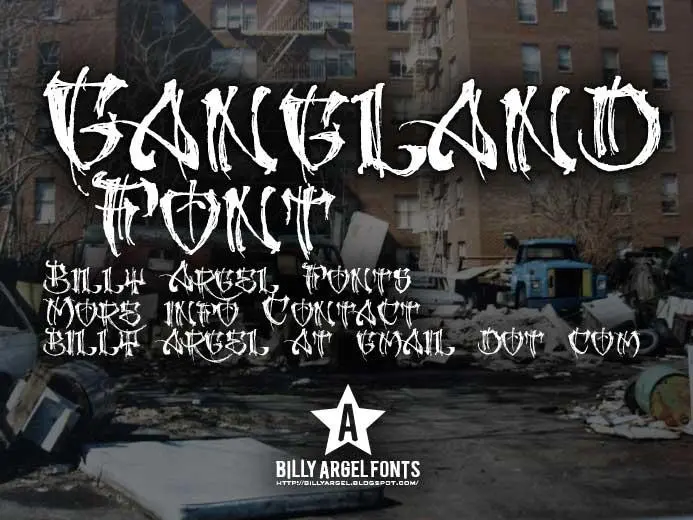
A GANGLAND Font é uma elegante fonte Brush, criada pelo designer Hamilton. Ela traz uma mistura única de sofisticação e liberdade artística para qualquer projeto que você escolha adicionar à sua portfolio. Com traços suaves e leves, esta fonte oferece um toque autêntico e pessoal a suas criações. Perfeita tanto para títulos quanto para o texto interno de um design, ela também se adequa perfeitamente a logotipos criativos ou marcas de negócios. Seja você designer gráfico, ilustrador ou qualquer profissão relacionada à arte visual, GANGLAND Font certamente será uma opção valiosa para adicionar ao seu arsenal. Combinada com o bom gosto e habilidade do seu próprio estilo, esta fonte é um atalho direto para aprimorar sua identidade visual. O designer Hamilton sabiou desenvolver uma fonte que não apenas oferece beleza, mas também personalidade. A GANGLAND Font, com suas linhas suaves e características distintas, é ideal tanto para iniciantes quanto para profissionais experientes na arte da design digital.